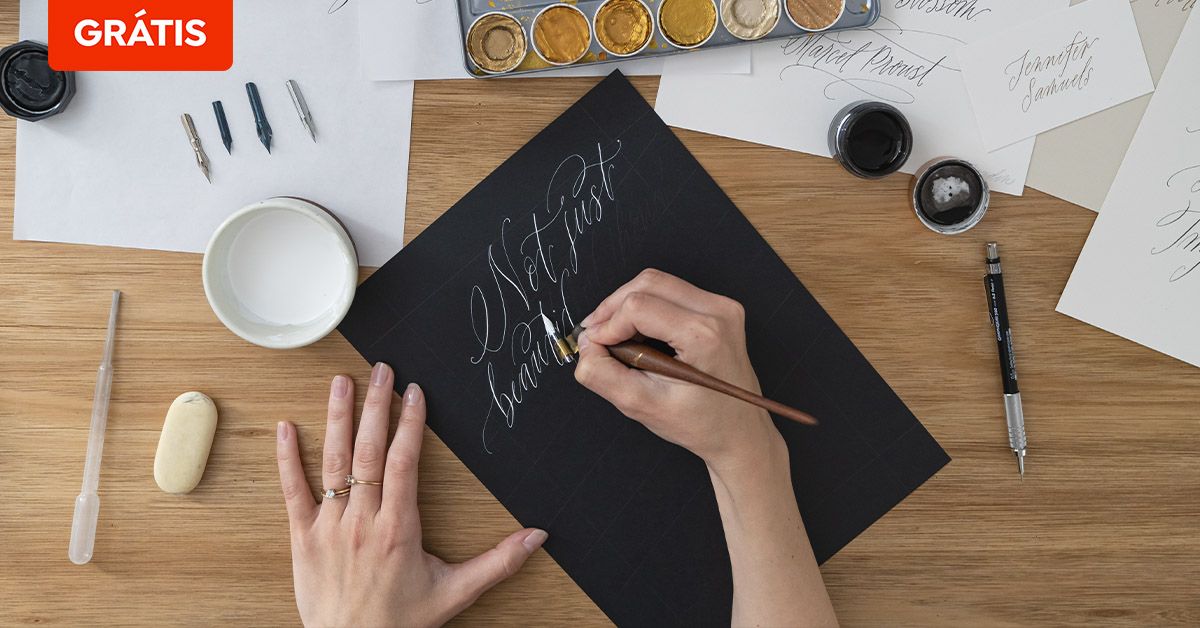
10 aulas gratuitas de tipografia essenciais em 2022
Aprenda como criar tipografias e dominar os elementos básicos do design de letras, seguindo estes conselhos fundamentais
Quer aprender como dominar diferentes técnicas tipográficas? Então, não pode perder estas aulas gratuitas ministradas por grandes profissionais da área.
A escolha e criação de uma tipografia vai muito além da estética, abraçando questões como leitura, espaçamento, sentimentos, emoções e traços capazes de adicionar inúmeras camadas de significado.
Para dominar esta arte, você precisa entender os aspectos essenciais de uma letra funcional, quais as melhores escolhas para contextos diferentes e como potencializar suas criações.
Nas aulas grátis que apresentamos a seguir, diversos especialistas ensinam técnicas básicas de como trabalhar com tipografia para criar designs e logos impactantes capazes de comunicar muito mais do que somente a forma estética.
1. Aula grátis: Ao pé da letra: vocabulário tipográfico 1
Para começar os seus estudos de tipografia, a aula Ao pé da letra: vocabulário tipográfico 1, parte do curso Fundamentos da tipografia de A a Z, é perfeita.
Nela você aprenderá que letras têm olhos, pernas e braços. Também têm ascendentes, bojos e contraformas. O designer gráfico e designer de lettering Álvaro Franca explica o vocabulário essencial para analisar fontes e formas de letra.
2. Aula grátis: O poder da tipografia
As letras possuem a capacidade visual de nos transportar para uma memória, um sentimento ou emoção, antes mesmo de entendermos o conteúdo que representam. É o que defende o designer gráfico e tipográfico Carlos Mignot.
Na aula O poder da tipografia, parte do curso Branding tipográfico: como criar logos memoráveis do zero, você aprenderá quais atributos são representados pelo desenho de letra com exemplos práticos e divertidos.
3. Aula grátis: Tipografia de desenho no modelo
Há mais de 12 anos a ilustradora Sarah King incorpora a tipografia em suas ilustrações. Ela já trabalhou para clientes como o New York Times, The Guardian e National Geographic, além da TASCHEN e o SFMOMA.
Na aula Tipografia de desenho no modelo, parte do curso Retrato tipográfico desenhado à mão, Sarah ensina como preencher com tipografias um molde de ilustração com dicas baseadas em seu próprio processo criativo.
4. Aula grátis: Os três níveis de uma fonte
Na aula Os três níveis de uma fonte, o designer de fontes Thomas Jockin ensina um processo simples de três etapas para analisar uma fonte.
O objetivo deste exercício, parte do curso Tipografia para designers: crie fontes para o mercado, é ajudar você a desenvolver um olhar apurado para refinar os designs de letras que criar.
5. Aula grátis: Conceitos básicos e códigos visuais de tipografia
Na aula Conceitos básicos e códigos visuais de tipografia, Daniel Barba López, diretor do estúdio de design Monotypo, aprofunda os conceitos básicos de tipografia como a anatomia das letras e suas estruturas.
Você aprenderá quantos deles têm uma estrutura geométrica básica, como elementos estruturais podem ser manipulados e como distinguir variações de tipografias. A lição faz parte do curso Tipografias personalizadas para design de logos.
6. Aula grátis: Retoque digital
Criar logos utilizando apenas letras pode ser um grande desafio e Elias Mule é um especialista nesta arte. Designer gráfico e diretor de arte, ele é fã de marcas capazes de dizer muito com pouco, onde contam não somente com a estética, mas também com a funcionalidade.
Na aula Retoque digital, parte do curso Design de tipografia para logos, ensina como você pode aproveitar ferramentas digitais como o Adobe Photoshop para agilizar o processo de criação e aperfeiçoar uma ideia.
7. Aula grátis: Ortopedia Primária
Na aula Ortopedia Primária, o designer editorial e tipográfico David Kimura ensina as regras ortotipográficas mais básicas e frequentes na maioria dos textos: scripts, figuras, letras maiúsculas e citações.
A lição ministrada por Kimura faz parte parte do curso Microtipografia: fundamentos de composição tipográfica.
8. Aula grátis: Tamanho da tipografia
O tamanho da tipografia é um aspecto essencial para que os textos sejam lidos bem. Na aula Tamanho da tipografia, a desenhista Gemma Busquets mostra as recomendações ideias para diferentes tamanhos de tela (computador, tablet ou smartphone).
A lição faz parte do curso Conceitos de tipografia para telas e nela você descobrirá as diferenças entre medir a tipografia em valores relativos ou absolutos e como usar as unidades de medida mais comuns: pixels e rems.
9. Aula grátis: Espaçamento e ritmo
Na aula Espaçamento e ritmo, os designers gráficos especializados em tipografias Damià Rotger Miró e Pedro Arilla ensinam os conceitos básicos e essenciais de espaço tipográfico e ritmo de uma letra.
A aula faz parte do curso Tipografia: construa sua palavra, no qual os designers ensinam como criar uma fonte tipográfica com a técnica do lápis duplo.